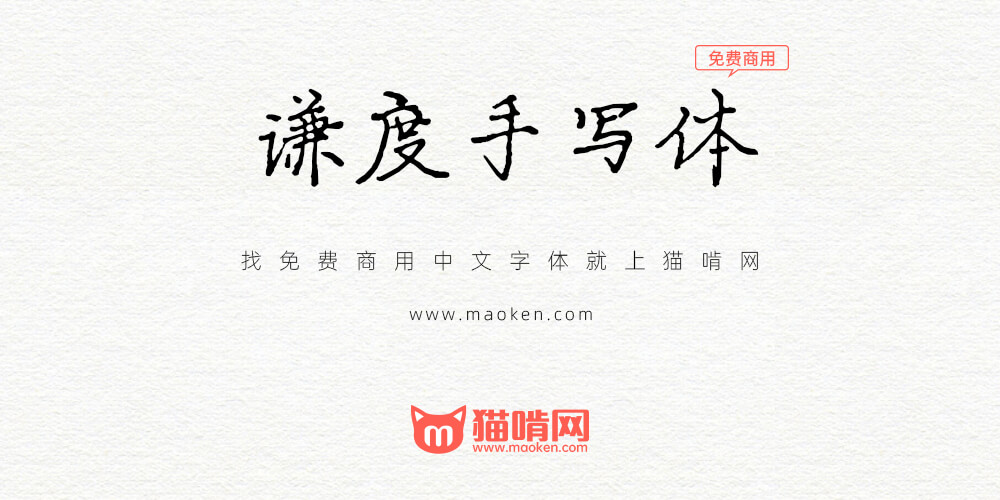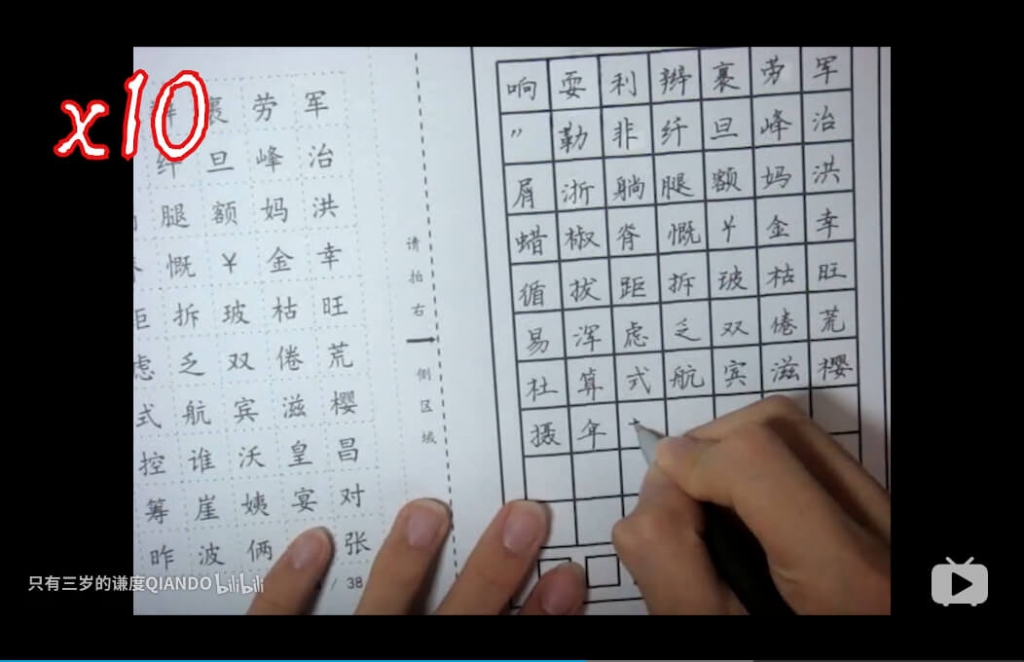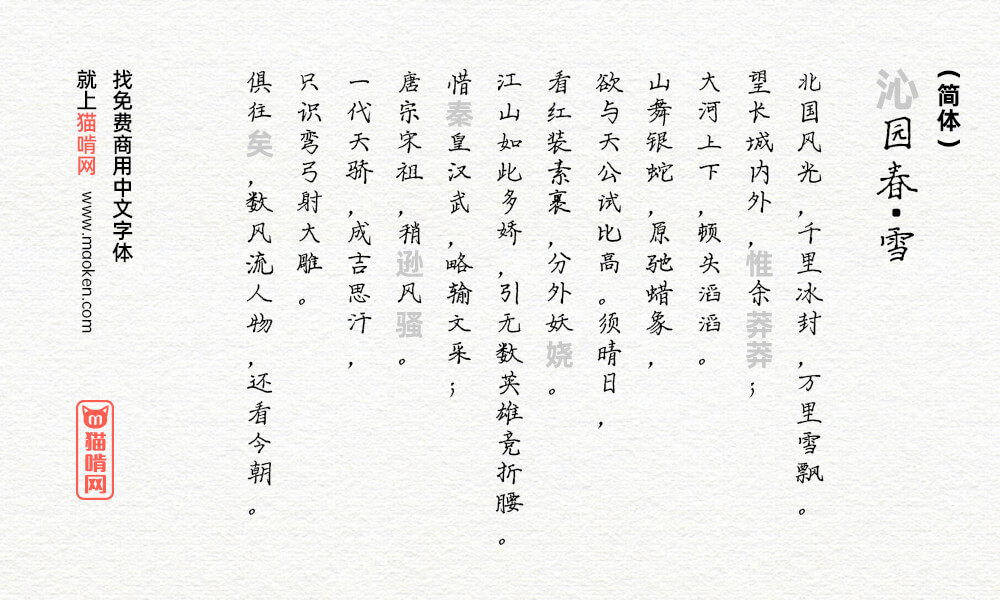
谦度手写楷体这款字体是B站的UP主三岁的谦度Chiando自己手写制作的一款字体。 这套字体用的时间说长不长说短不短,花费很多心思,一笔一画写了5000多个字写出来的。
谦度手写楷体是一款十分接地气的手写字体,字体就跟我们平时用圆珠笔写出来的一样。而字体写得也比较漂亮,干净整洁,值得推荐。而UP主也十分善心,这套字体完全可以免费商用!感激~
這是我見過 硬筆手寫體楷書中最好看的 噁心的北大計算機研究所